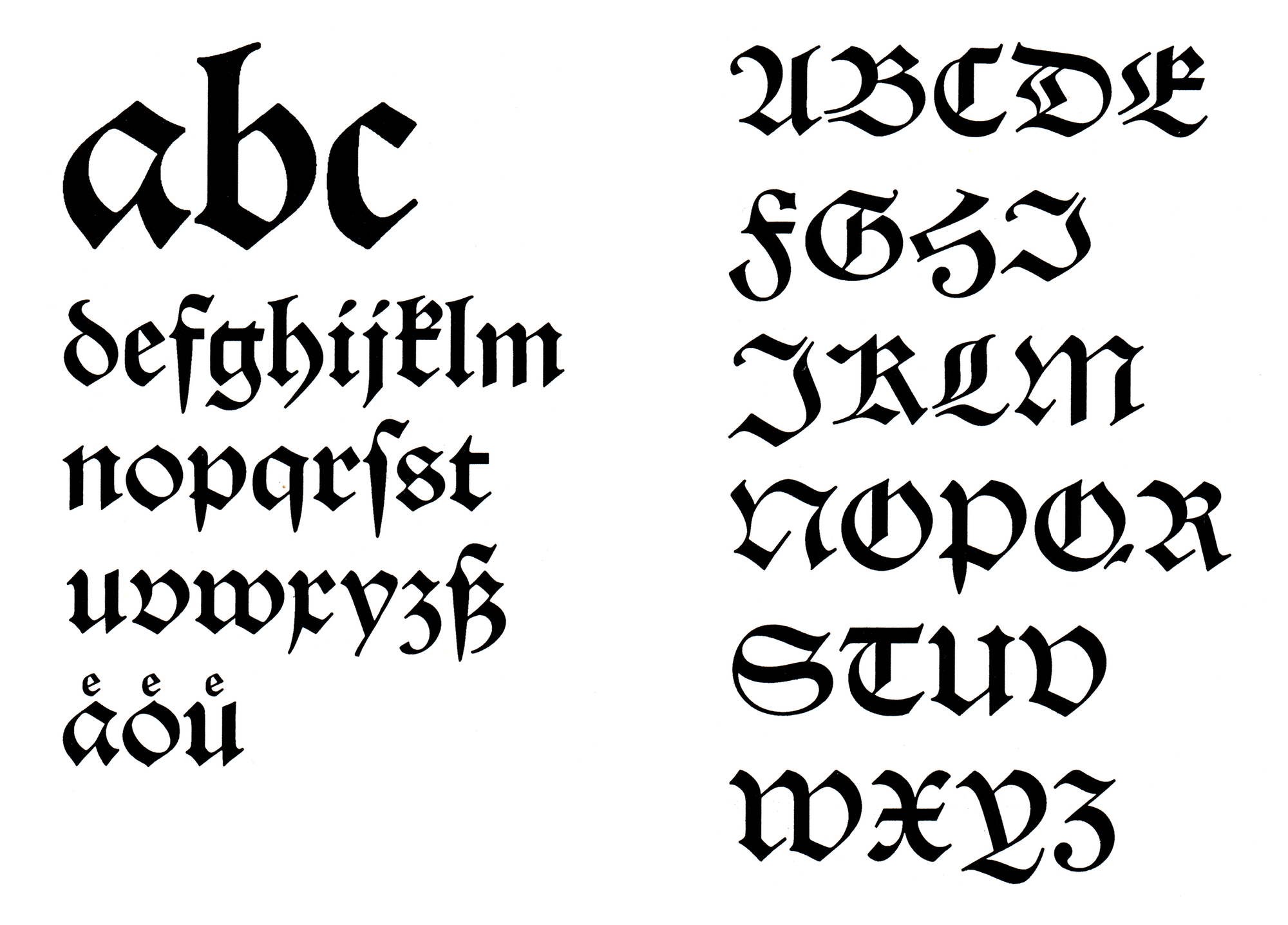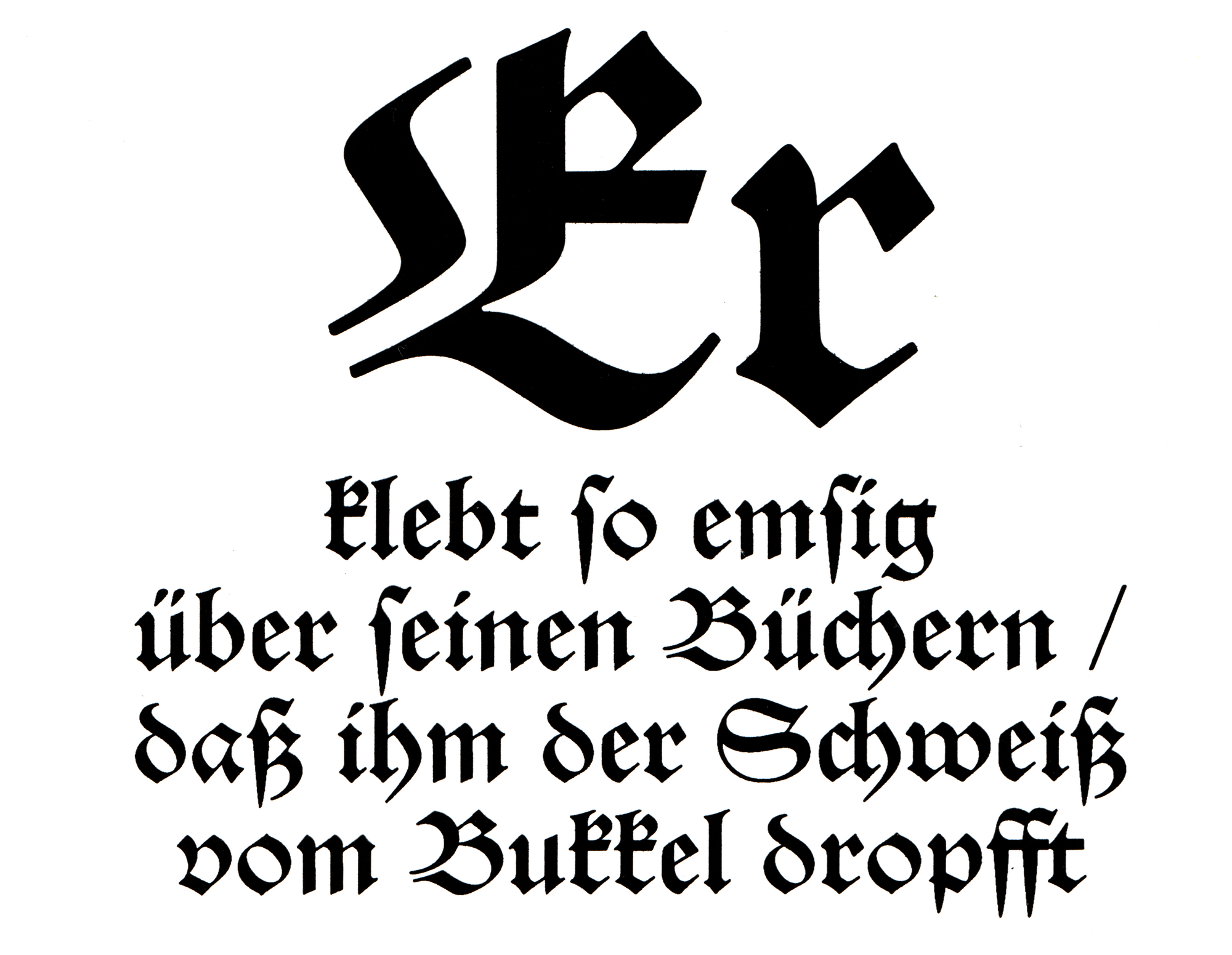
Font-Wiki: Typoart-Schwabacher
Die Fotosatz-Überarbeitung des Schwabacherstils durch Herbert Lemme orientierte sich an historischen Drucken. Anstelle der »falschen« Versalziffern, wie sie von anderen Schwabachertypen bekannt sind, wurden bei der Typoart-Fotosatzschrift Minuskelziffern eingesetzt.
Eine Digitalisierung wurde über Elsner+Flake in zwei optischen Größen (TB/TH) verfügbar gemacht.